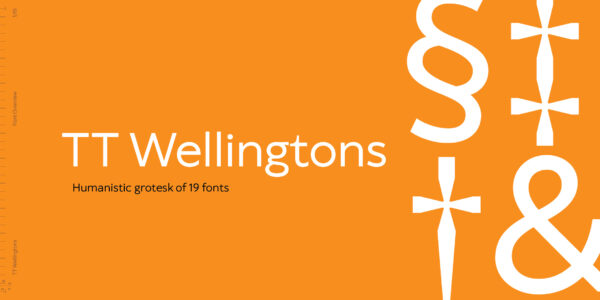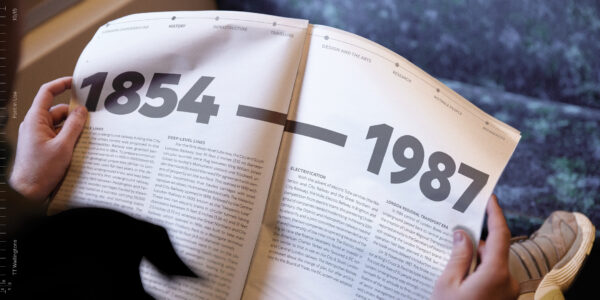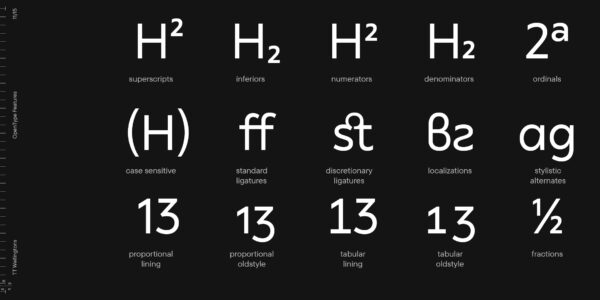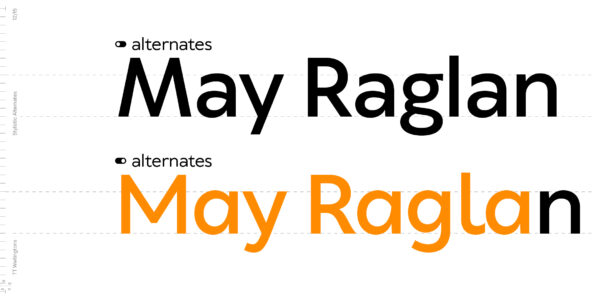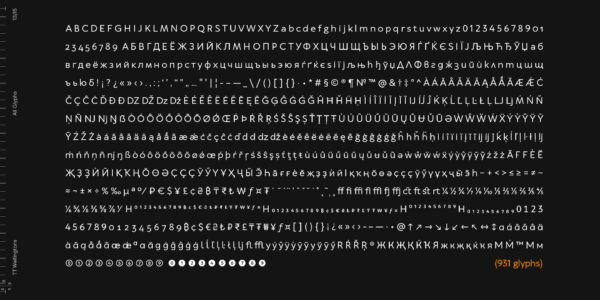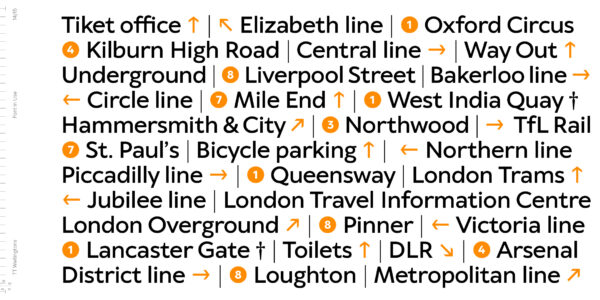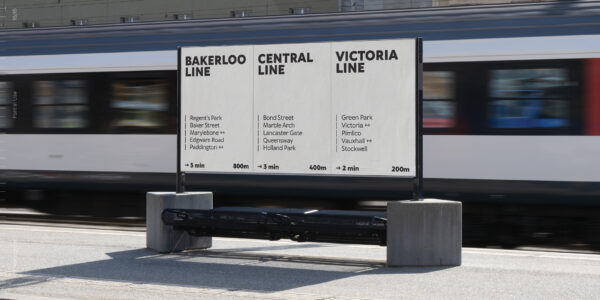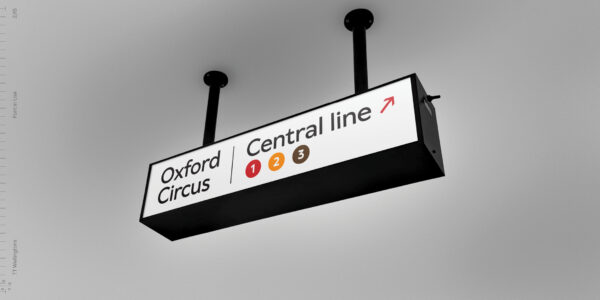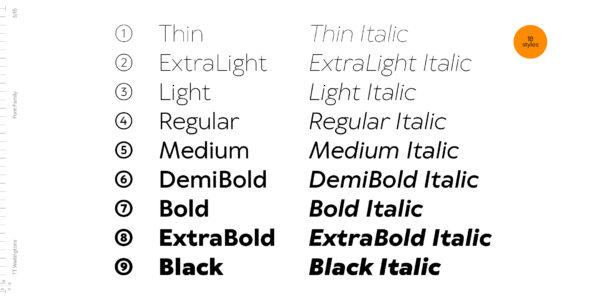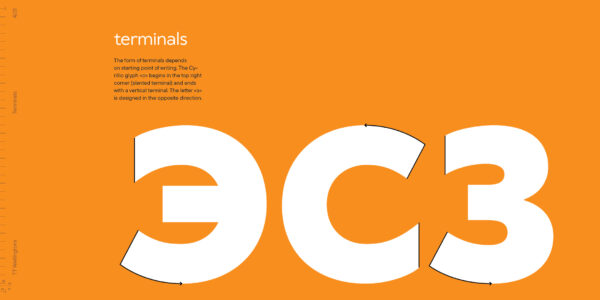
TT Wellingtons
TT Wellingtons — ТТ Веллингтонс
Произносится «ТТ Веллингтонс». «Wellingtons» — производное слово от названия города Wellington. Буквы «TT» являются аббревиатурой названия компании.
TT Wellingtons — гуманистический гротеск, формы которого отсылают к движению ширококонечного пера. Это современный шрифт с лаконичным и запоминающимся характером.
Представляем вам вторую версию гуманистического гротеска TT Wellingtons
Гуманистические гротески прочно ассоциируются с английской культурой начала 20 века. TT Wellingtons относится именно к этой категории шрифтов. Внутри шрифтового семейства TT Wellingtons встроен архетип широконечного пера. Как будто бы можно взять этот пишущий инструмент и написать каждый знак из шрифта. Этот факт делает данное шрифтовое семейство очень живым и человечным. В новой редакции шрифта в 2023 году мы сделали большую работу: увеличили знаковый состав, исправили пропорции всех знаков, поработали над детализацией контуров, подготовили шрифт для работы в любых типах интерфейсов. Фактически, это полностью новый шрифт, созданный для всех нужд современного графического дизайнера.
«Работа — лучшее лекарство от печали», — Шерлок Холмс
Английский и гуманистический
TT Wellingtons в новом воплощении!
Мы изменили в шрифте всё, от кассового состава до технического дополнения. Перерисовали каждый контур, доведя формы до совершенства. Главное осталось неизменным — перед вами современный шрифт с лаконичным и запоминающимся характером.
TT Wellingtons — это гуманистический гротеск, формы которого отсылают к движению ширококонечного пера. Пластичные линии букв обновлённой гарнитуры, присущие английским гуманистическим шрифтам XX века, выглядят актуально и живо в современных дизайнерских проектах.
TT Wellingtons 2023 года — шрифт, созданный с учётом новых технических требований.
● Расширенный кассовый состав.
Мы добавили 358 новых символов в каждое начертание, увеличив количество знаков до 913. Появились буквы расширенной кириллицы и латиницы, новые знаки валют и математических символов, знаки с диакритикой и стрелки.
● Обновлённый состав OpenType фич.
Теперь в шрифте 35 функциональных и удобных для дизайнеров фич, включая стилистические альтернативы и фичи локализации.
● Больше языков.
Новая версия поддерживает более 230 языков.
● Вариативное начертание.
Теперь можно создавать уникальное начертание, меняя шрифт по двум осям вариативности: жирности и наклона. Всего в шрифте 19 начертаний: 9 прямых, 9 наклонных и вариативный шрифт.
● Новые контуры.
Мы проанализировали символы во всех начертаниях, чтобы сделать шрифт ещё гармоничнее. В новой версии улучшены формы терминалов и срезов, например в знаках a, c, g, j, y и цифре 2. Дополнительно привели к единообразию контраст знаков во всех начертаниях, а части знаков, таких как b, d, q, p, придали гуманизма, проработав над влитиями.
● Новая диакритика.
Новые знаки с диакритикой выглядят эстетичнее, а работать с ними ещё удобнее.
● Новые формы.
Некоторые символы получили совершенно новую форму. Например, буквы a и g теперь имеет одну логику во всех начертаниях, а символ Q выглядит более лаконично благодаря новой форме изогнутого элемента.
● Совершенные италики
Знаки в наклонных начертаниях были практически полностью перерисованы. Новые италики безупречны с графической и технической сторон.
Новый TT Wellingtons удобен и красив везде, где необходима эстетика: в заголовках или текстовых блоках, в веб-индустрии или печатных материалах, в оформлении фильмов, видеороликов и вывесок.
Марина Ходак
Анна Тихонова
Анастасия Погорелова
Анастасия Врублевская
Что изменилось в шрифте:
• Добавили 358 новых символов в каждое начертание, увеличив количество знаков до 913.
• Теперь в шрифте 35 функциональных и удобных для дизайнеров фич, включая стилистические альтернативы и фичи локализации.
• Новая версия поддерживает более 230 языков.
• Теперь можно создавать уникальное начертание, меняя шрифт по двум осям вариативности: жирности и наклона.
• Улучшили формы терминалов и срезов, например в знаках a, c, g, j, y и цифре 2.
• Привели к единообразию контраст знаков во всех начертаниях, а части знаков, таких как b, d, q, p, придали гуманизма, проработав над влитиями.